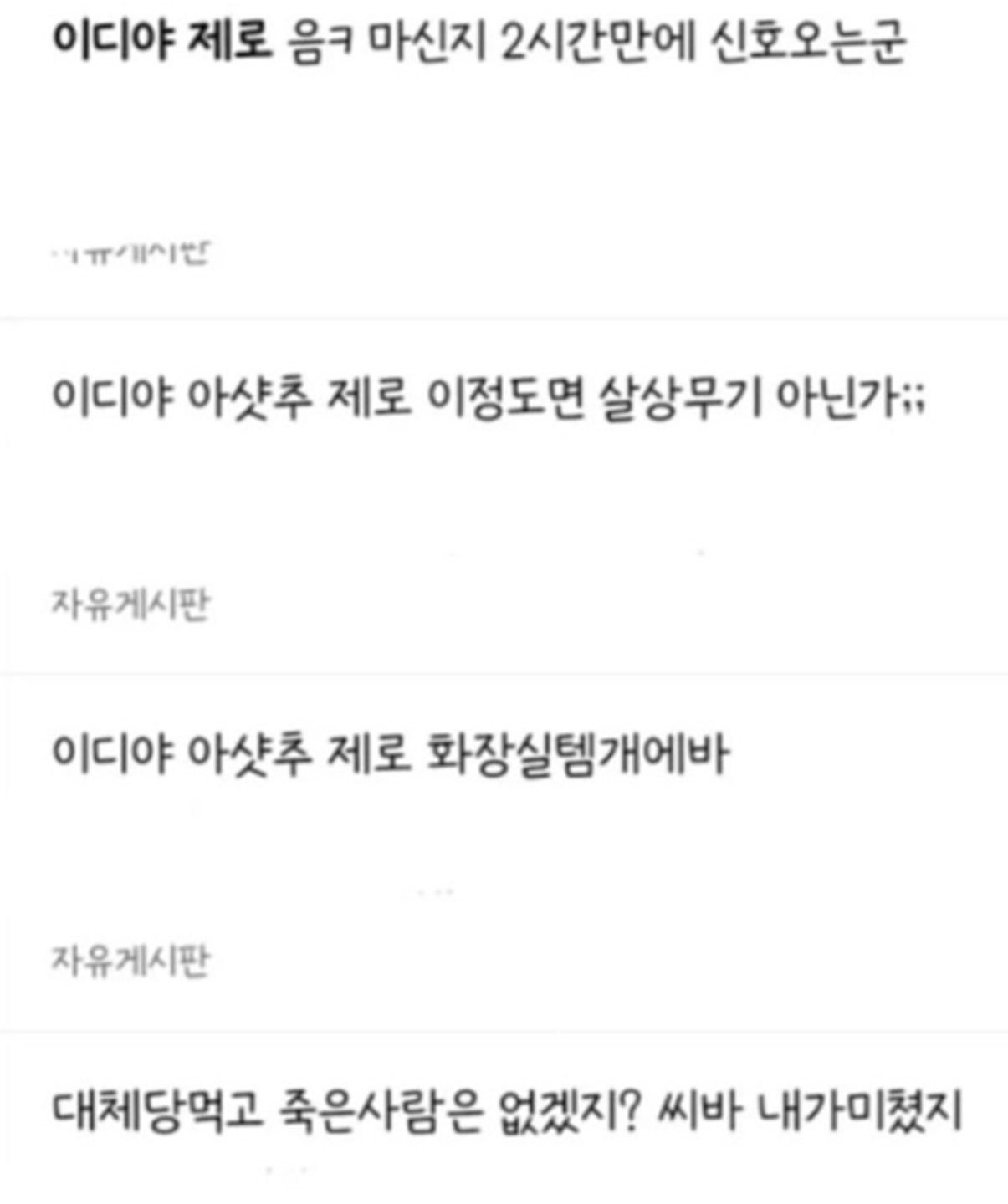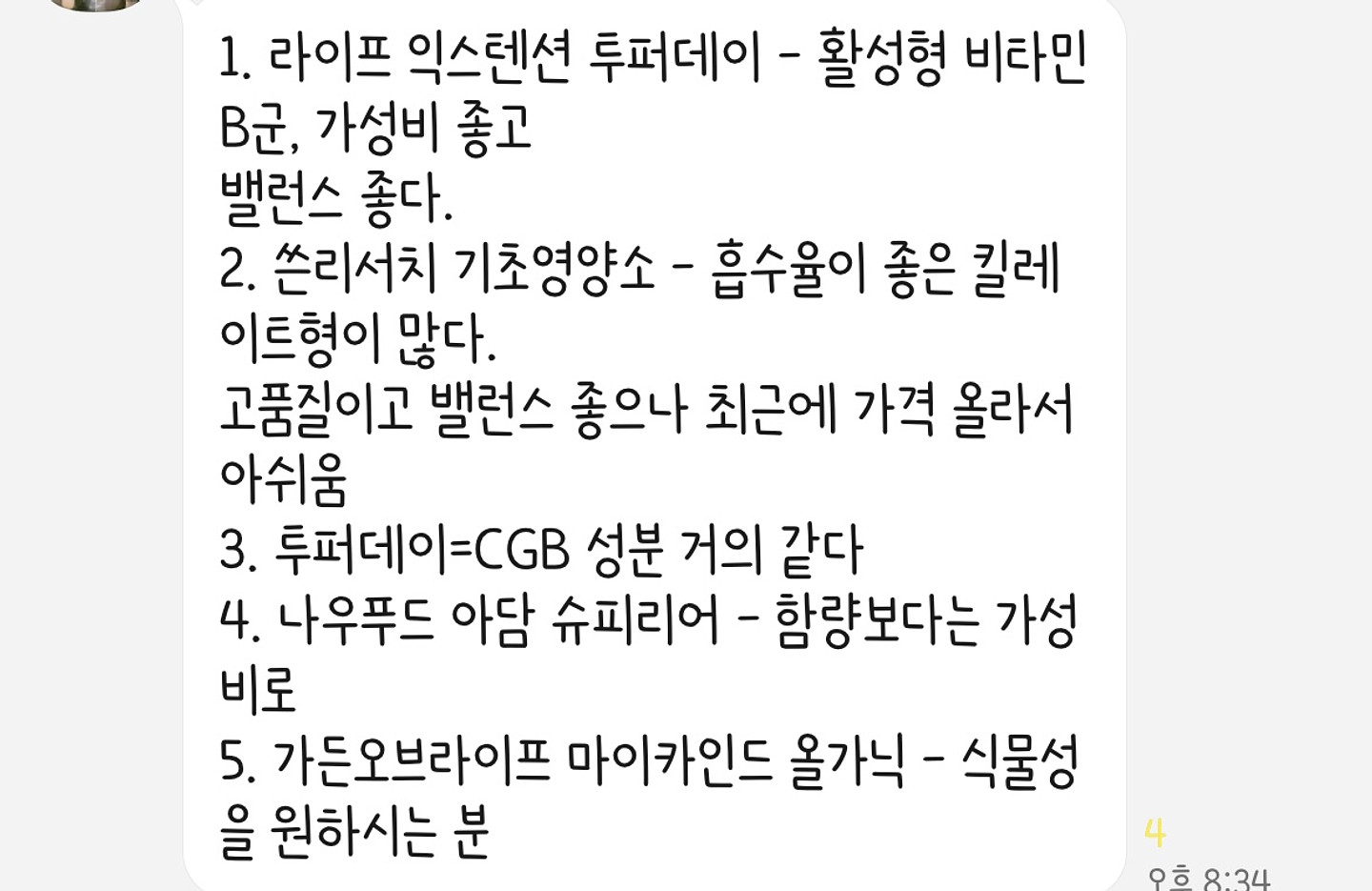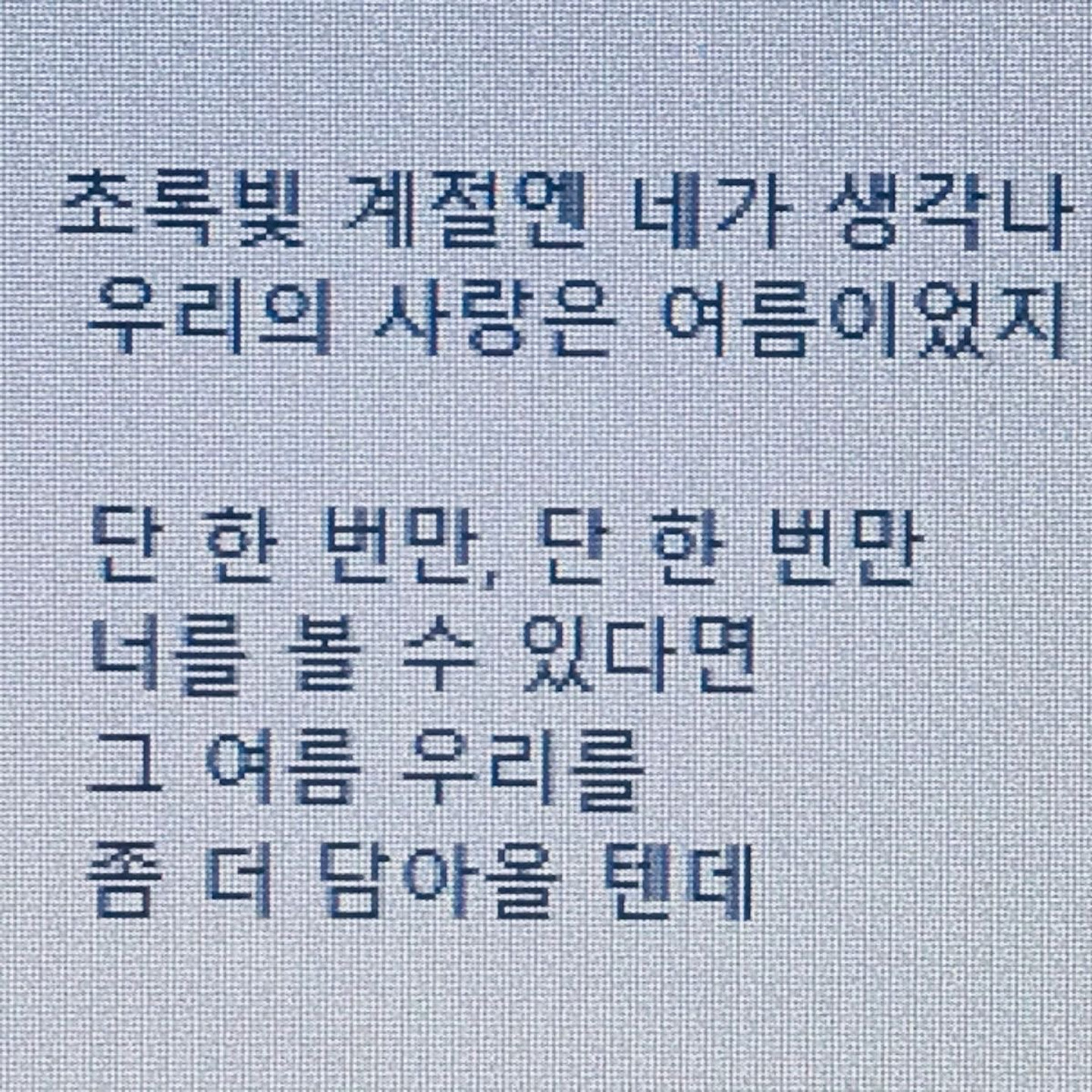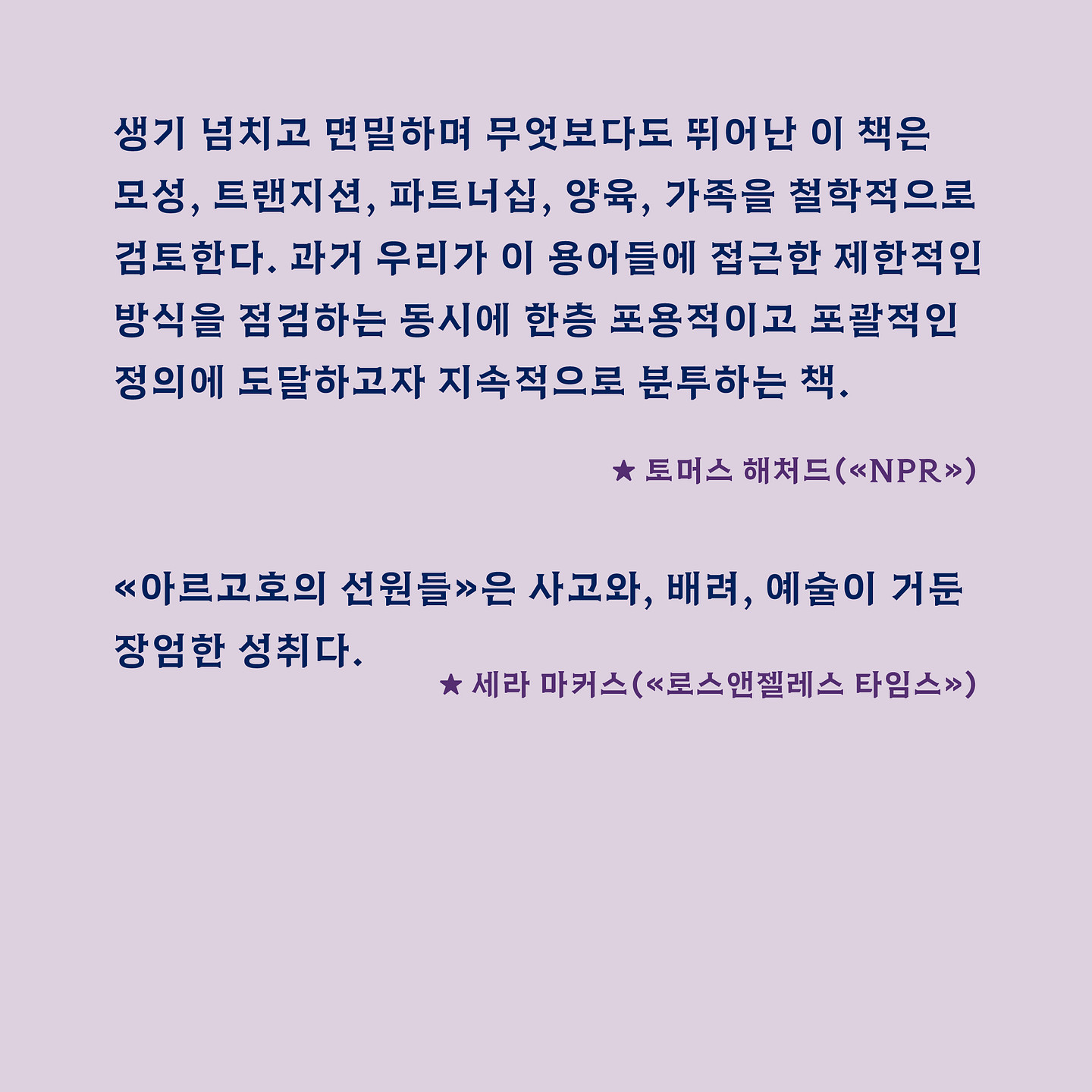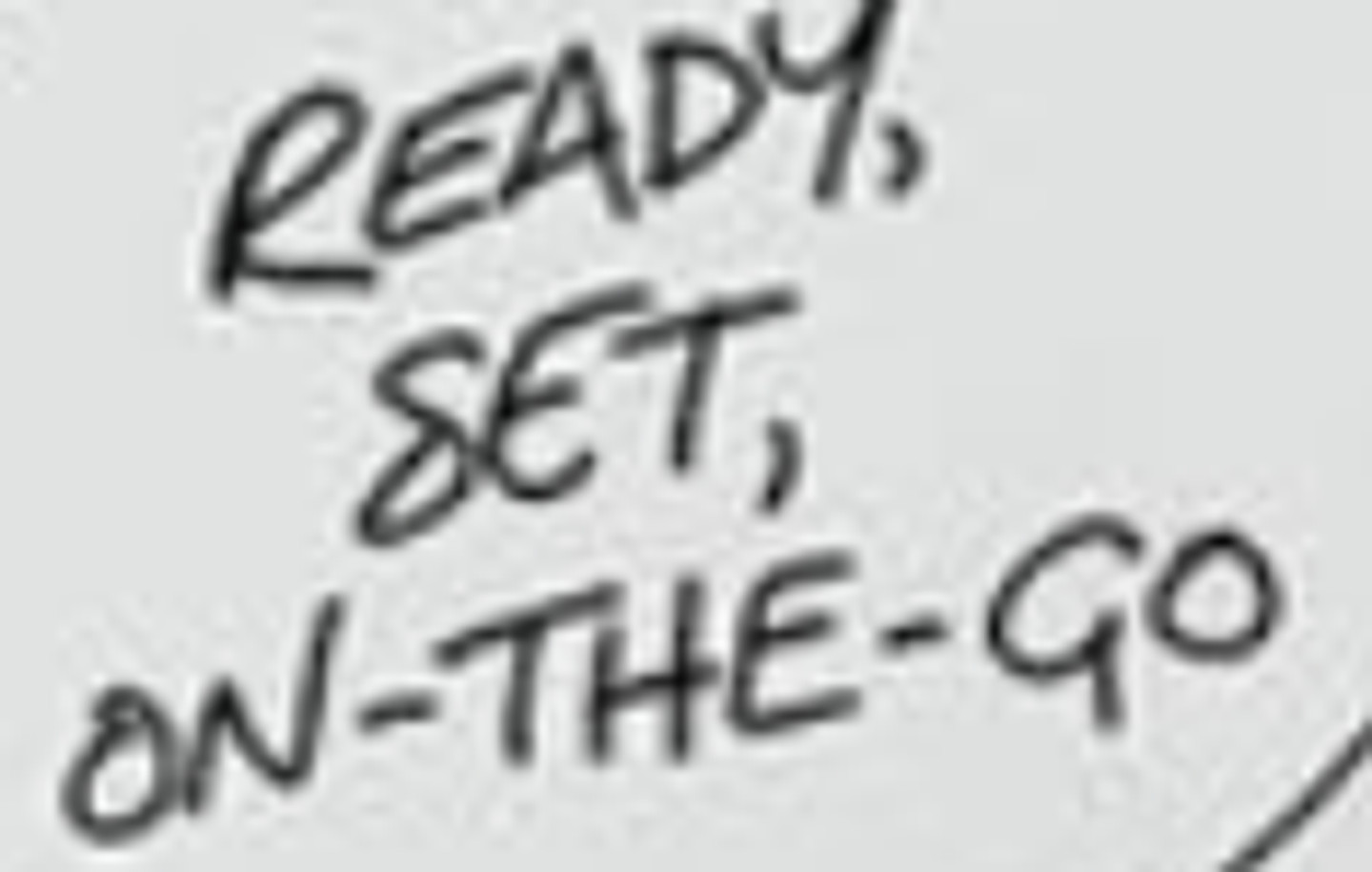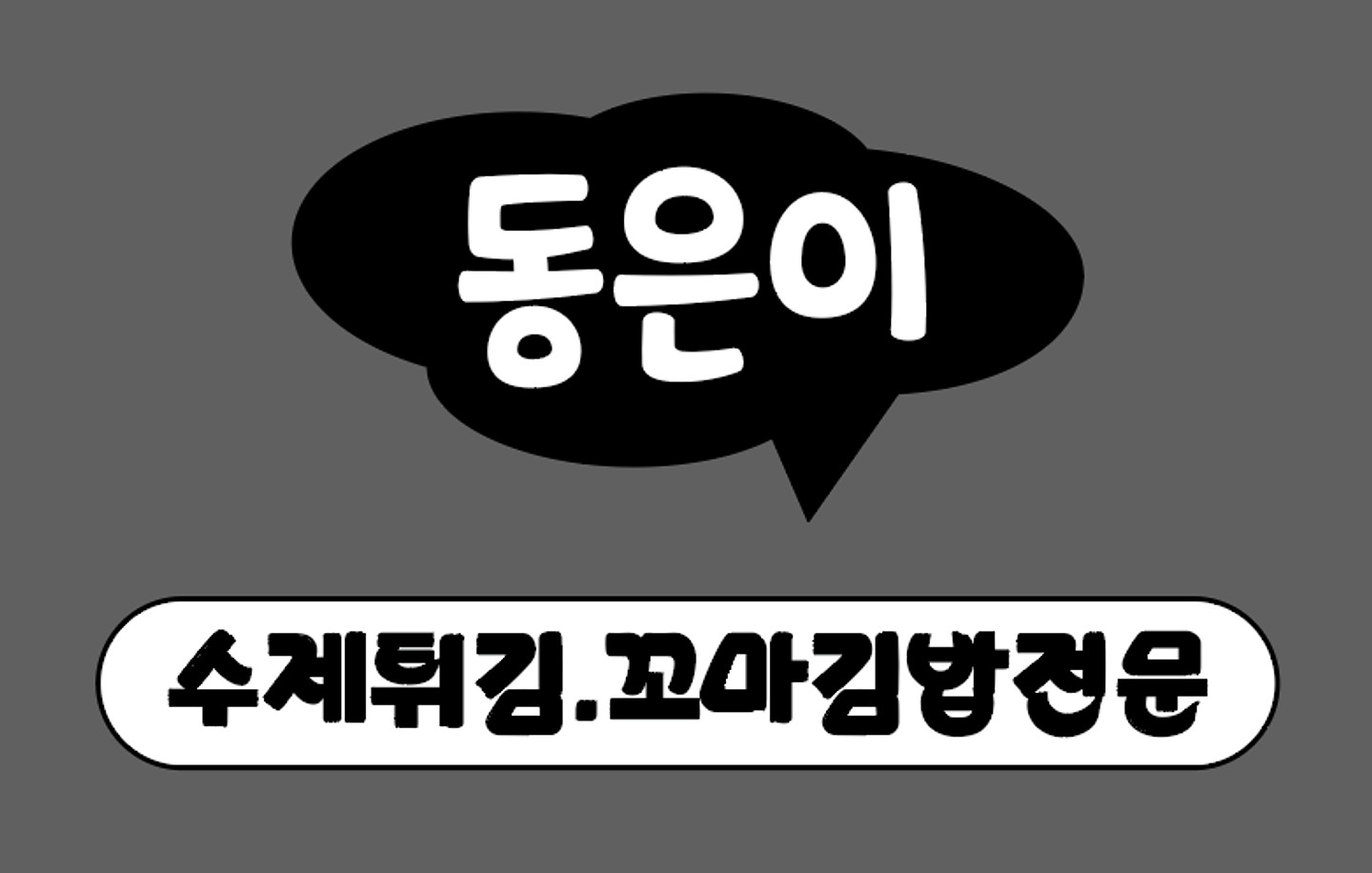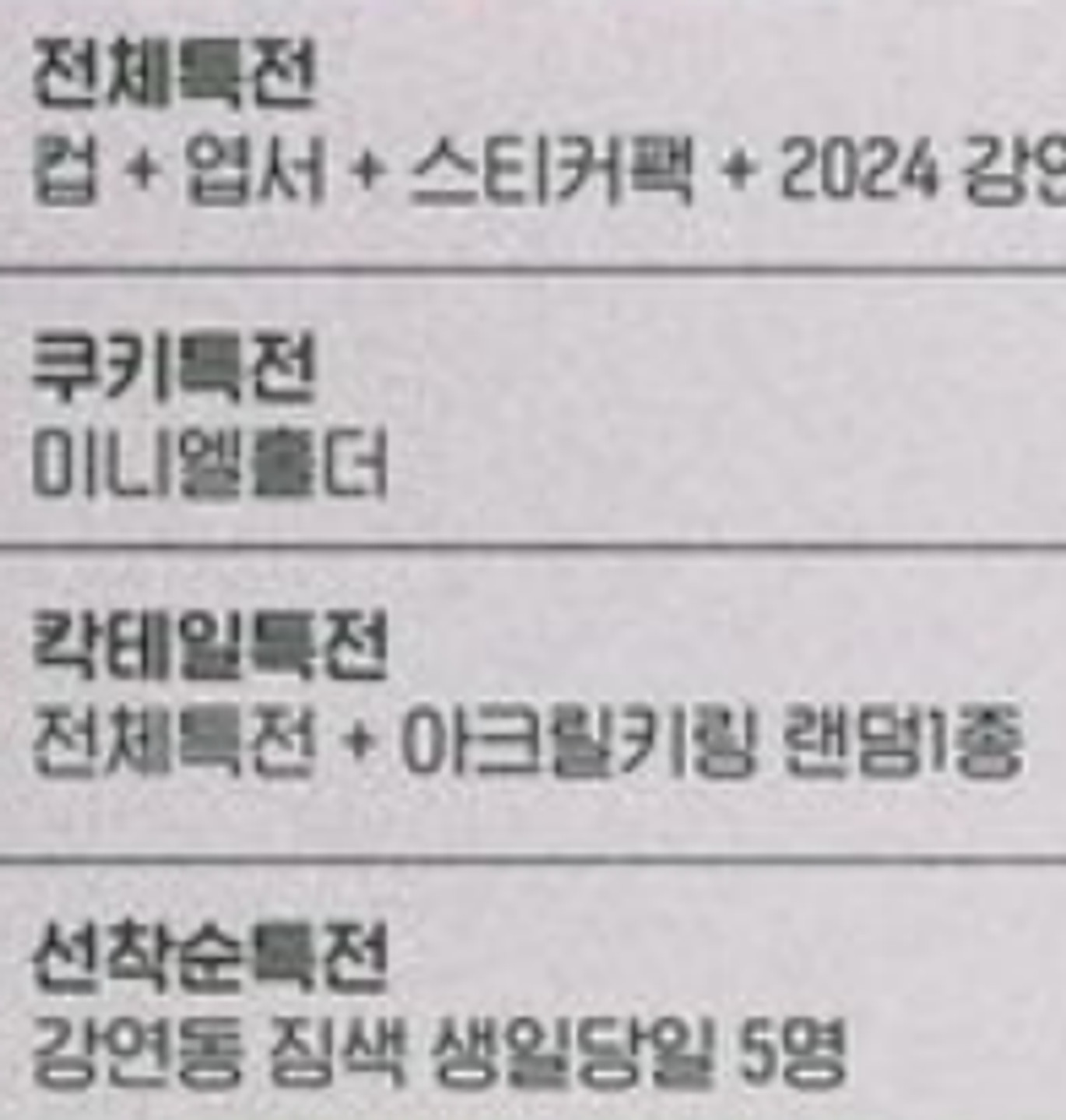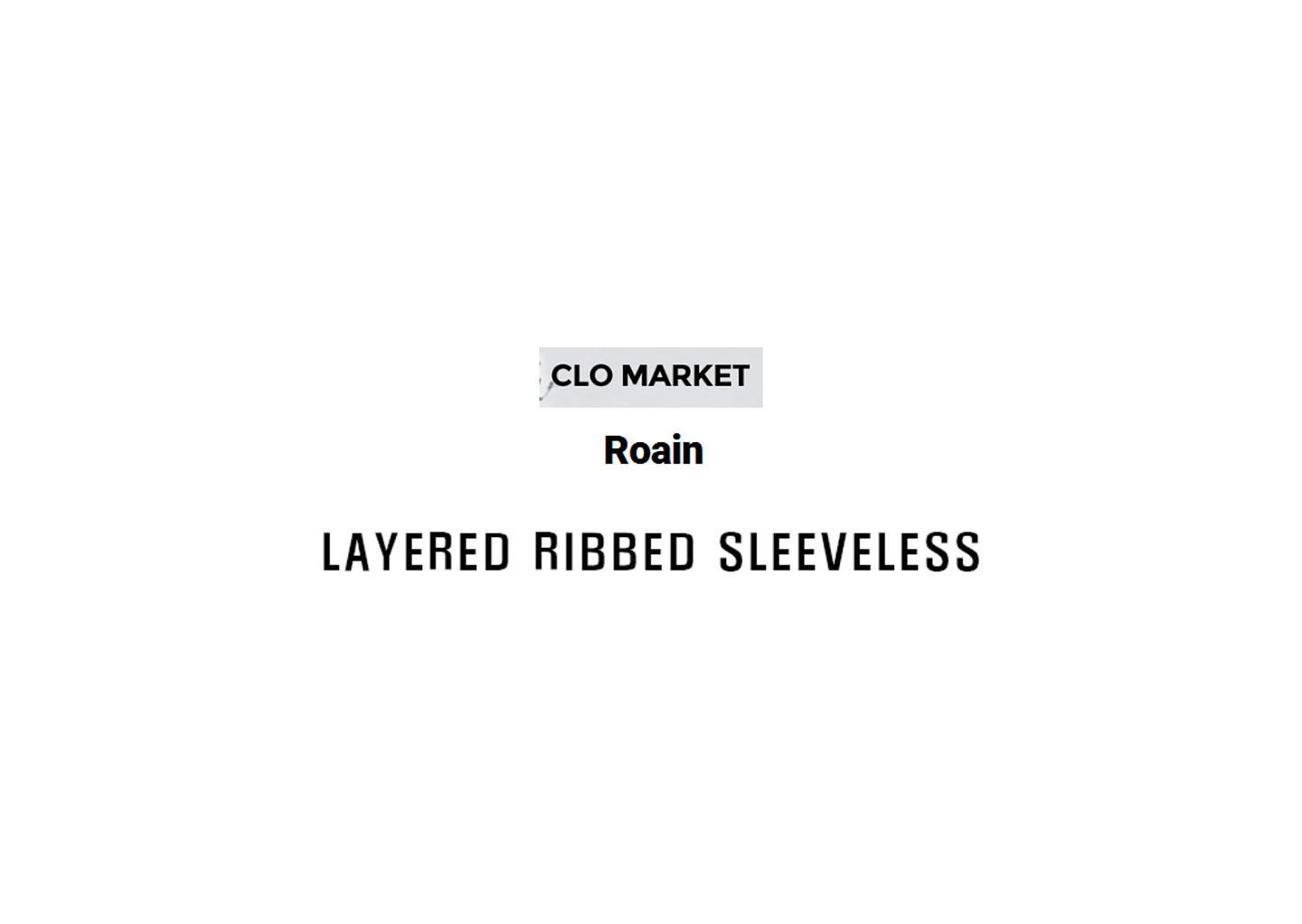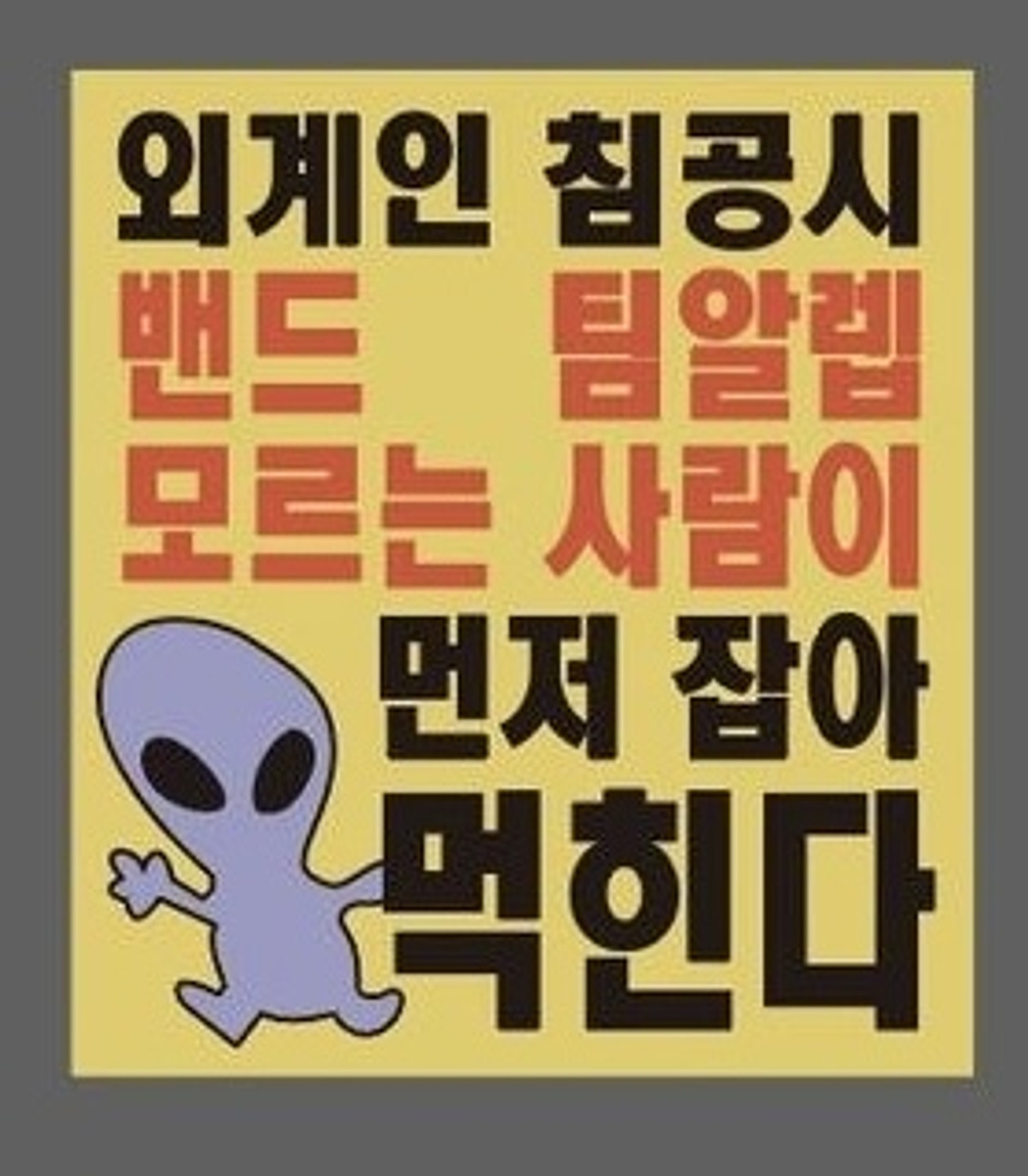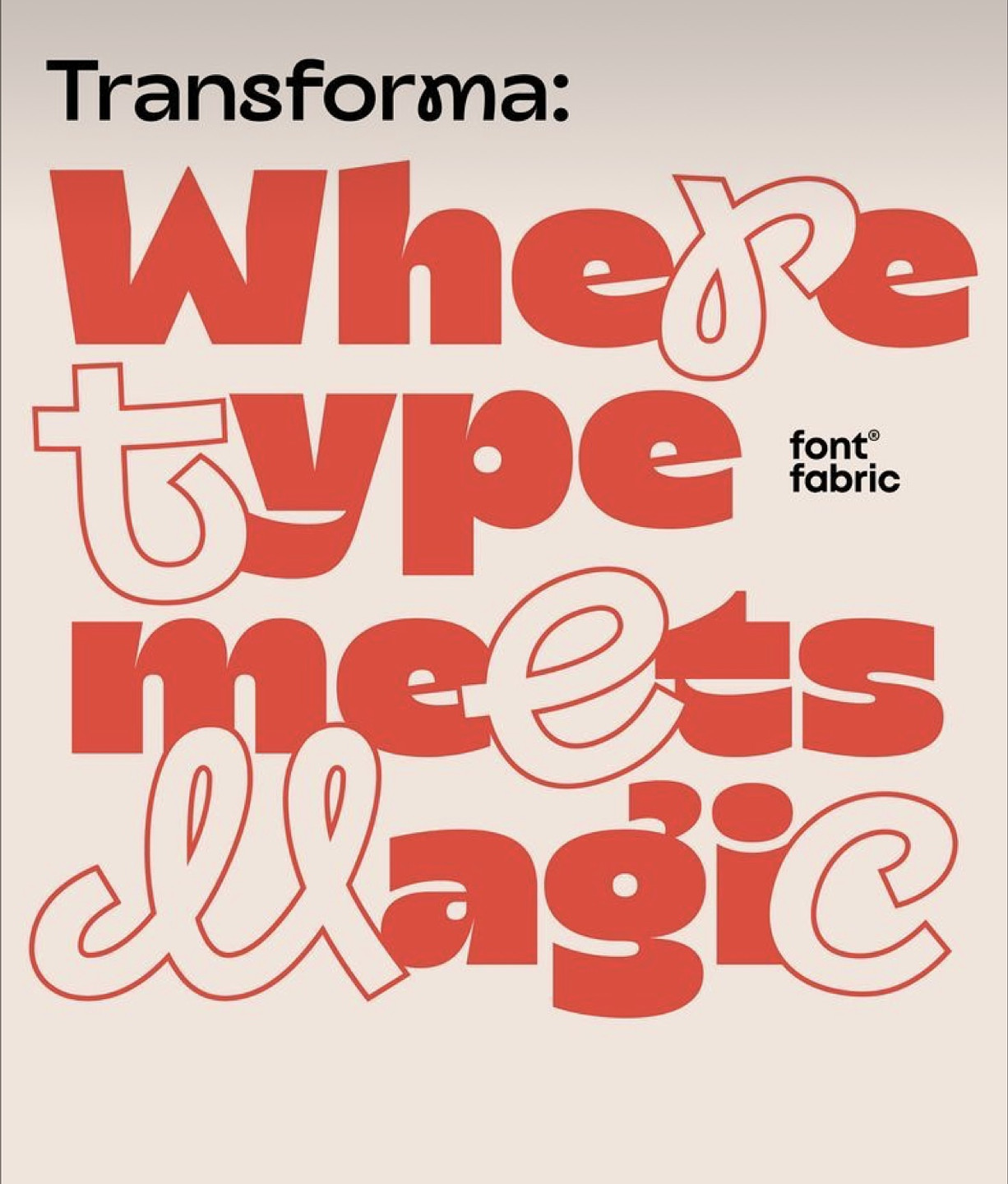
인스타에서 본 폰트인데 어떤 폰트인지 너무 궁금합니다!!!
어떤 폰트인가요
저기 한글 [대한민국정책센터] 무슨 폰트일까요?
폰트 뭘까여
진짜 손글씨같으면서 가독성 넘좋아서 어떤폰트인지 너무 궁금합니다🥲
이 폰트 알 수 있을까요ㅠㅠ 전부터 찾고 있는데 못 찾겠습니다ㅠㅠ
빠르고 재미있는.. 무슨 폰트 일까요?
무슨 폰트인지 알 수 있을까요? ㅠㅠ
무슨폰트일까요?ㅠ
겨울 일기모음이랑 아래 글 모두 다 같은 폰트같은데 무슨폰트인가요?
이 폰트 뭘까요, ,?
뭔지아시는분
이 폰트 이름 알 수 있을까요? 이미지 검색이 안 됩니다..! ㅠㅠ
티빙 오리지널, 또다른 시작 글씨체 뭔가요?
엔시티 위시 미라클 활동에서 쓴 폰트 알려주세요!!!!!!!!!!
매치데이 폰트 뭐인가요?
무슨 폰트일까요?ㅠㅠ
큰 문구랑 작은 문구 폰트가 뭔가요??
글씨체 이름 알 수 있을까요? 감사합니다 :)
이거 무슨 폰트인지 아시는분..
이거 무슨 폰트인가요? 산돌 검색해도 안나오네요 ㅜ
이거 어떤 폰트일까요? 스픽 광고입니당
위 사진처럼 세련되고 깔끔하면서 소문자 e가 대각선으로 되어있는 폰트 이름이 무엇인가요?
스텐실 스타일 글꼴인데 어떤 폰트인지 알 수 있을까요?
이 폰트가 궁금합니다. 무슨 폰트인지 아시는 분?!
작은 문구 폰트랑 큰 문구 폰트 둘 다 궁금합니다!
이거 무슨 폰트인가요? 생카 포스터에 많이 쓰이던데!
마이리얼트립 폰트인데 pretendard 인줄 알았다가 따옴표 모양이 달라서 문의 드립니당
메인폰트 알려주세요!!
폰트 궁금합니다!!
생명의 땅 으뜸 전남 / 기본 폰트를 변형해서 만든것 같은데 기본 베이스 폰트가 뭘까요?
이 폰트 아시는 분 있을까요..
자글자글한 테두리가 있는데 궁금해요!
유튜브 최화정 채널에 나오는 자막 폰트 이름 알 수 있을까요?!
이런식으로 글자 가운데 심지처럼 있는 폰트가 있을까요?! 한글이나 영문 모두 좋습니다
이 폰트 아시는분ㅜ
무슨폰트인지 알 수 있을까요?
무슨 폰트에요
요 폰트몰까요?
이 폰트 뭔가요? 산토끼체는 아닌 거 같아요
무슨 폰트인가요???
이폰트뭔가용
이렇게 둥글둥글한 폰트 아시면 답변 부탁드립니다 .. ㅜㅜ 감사합니다!
위 폰트 무슨폰트 인지 알 수 잇을까요????
안녕하세요 고수님~ 이 손글씨 폰트이름을 알수 있을까요?
무슨폰트일까요...
이거 무슨폰트일까요??
시옷 형태가 독특한 이폰트의 이름이 너무 궁금합니다ㅠㅠ 도와주세요!